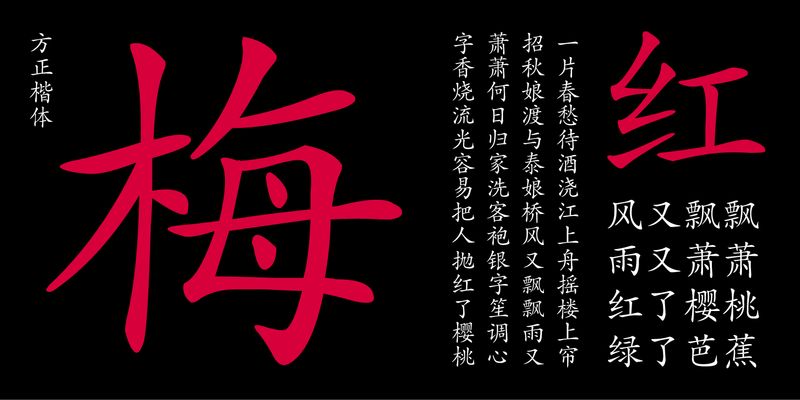
Fāng Zhèng Kǎi Tǐ는 Shanghai Institute of Printing Technology의 “Chinese Standard KaiTi” 스크립트에서 유래했습니다. 1940년대에 만들어진 오리지널 “Chinese Standard KaiTi”는 중화인민공화국 건국 이후 주로 사용된 목판 인쇄 버전이었습니다. Shanghai Font Factory 1, Shanghai Institute of Printing Technology 및 기타 기관에서 여러 차례 개선 작업을 수행했으며, 간체 버전을 추가했습니다. Fāng Zhèng Kǎi Tǐ 의 구조는 균형이 잘 잡혀 있고 획은 둥글고 부드러우며 가로 세로 획의 굵기는 변화가 거의 없습니다. 이 글꼴은 신문, 잡지, 책에 널리 사용되며 교과서에 가장 일반적으로 사용됩니다.